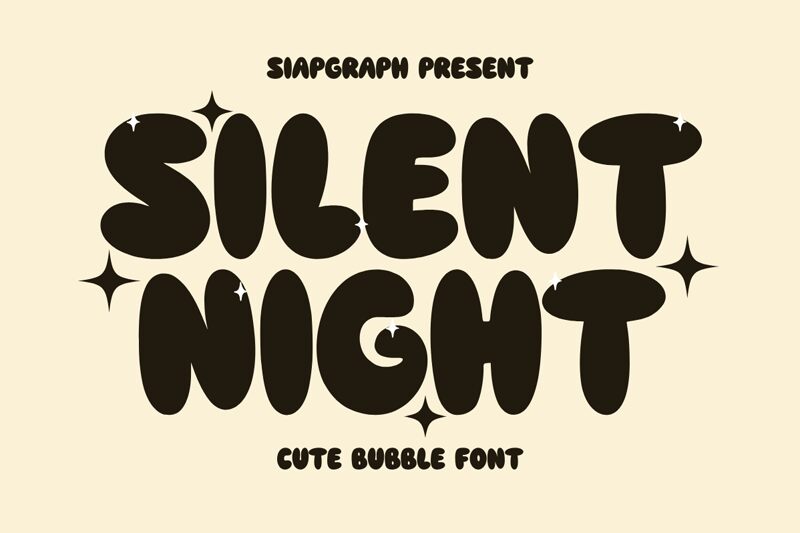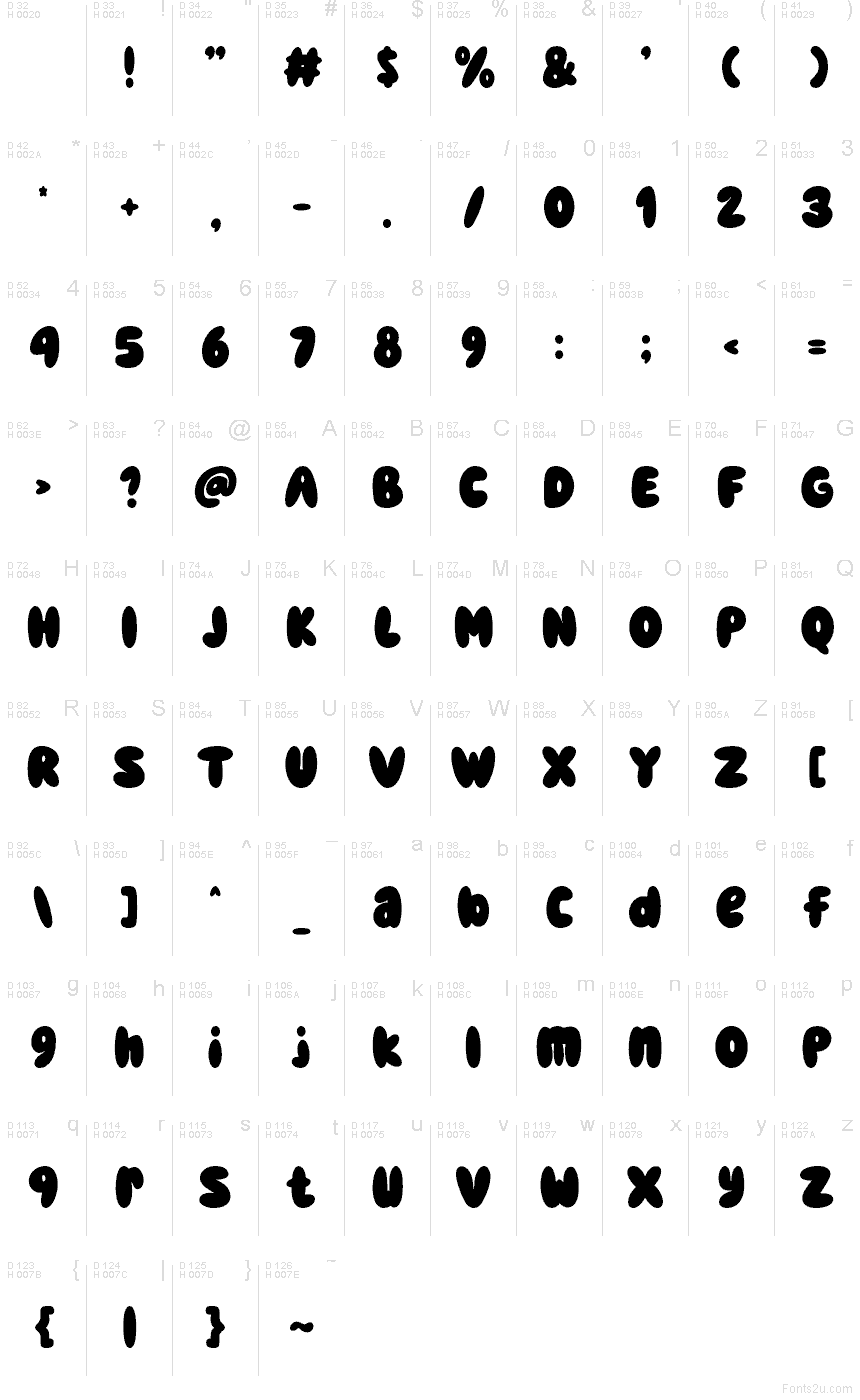
Silent Night от SIAPGRAPH STUDIO - это бесплатный мультяшный дисплейный шрифт, созданный на основе раздутых, напоминающих фасолины силуэтов, которые придают буквам мягкий и объемный вид. Закругленные формы гармонично смотрятся в любом наборе, создавая бодрую «подушечную» текстуру, в отличие от резкого комиксного стиля.
Благодаря своей массивности шрифт отлично подходит для коротких заголовков на детской упаковке, этикетках конфет, приглашениях на день рождения, дизайне стикеров и игривых постах в соцсетях. Он также станет прекрасным акцентом для превью на YouTube или праздничных вывесок, где эти «надутые» формы позволяют словам выглядеть как графические элементы, а не просто текст.